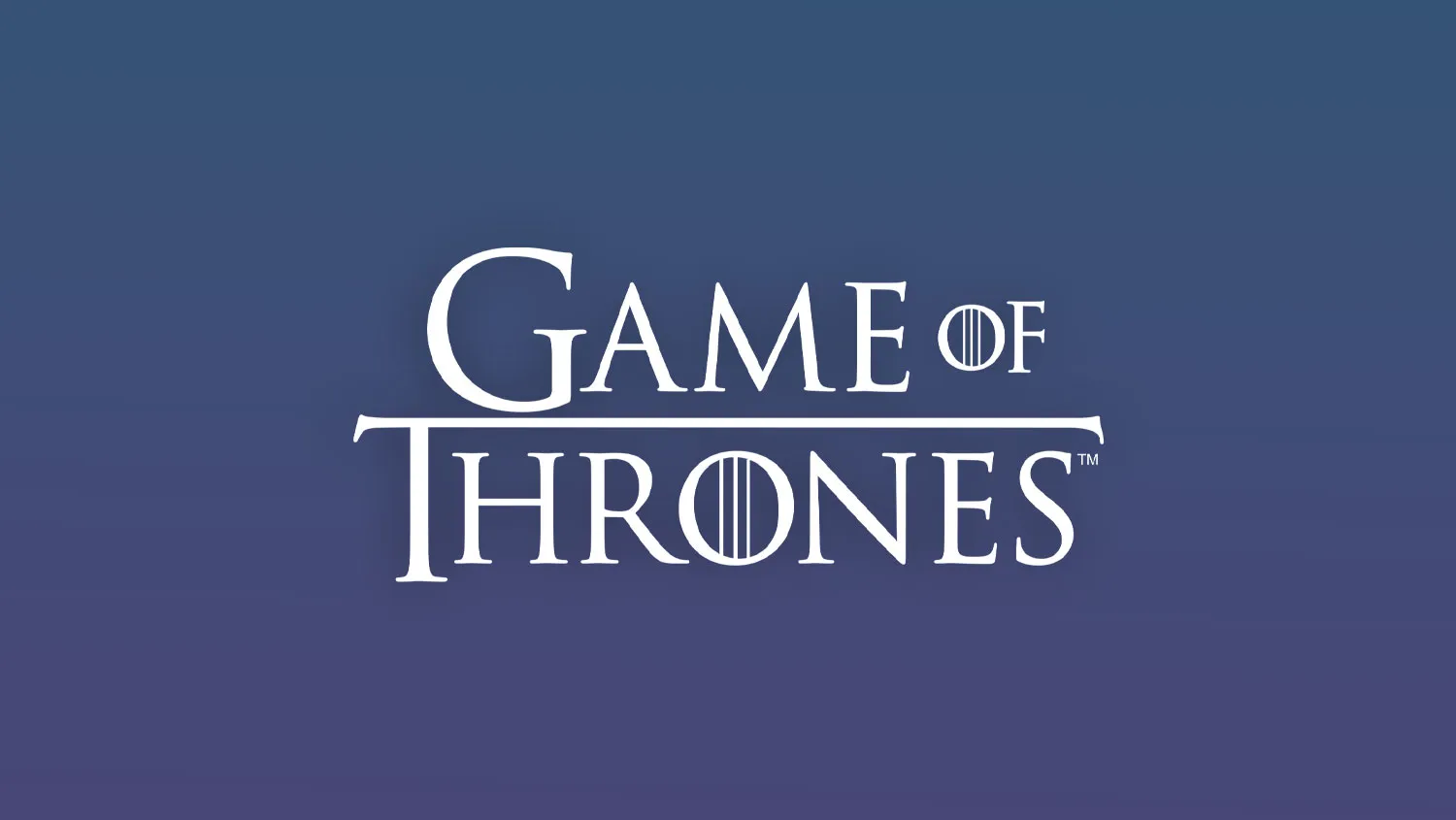
I font delle serie tv più famose
Vediamo insieme cosa si nasconde dietro i font di alcune delle serie tv più famose. Font e logotipi che hanno contribuito in qualche modo a rendere queste serie iconiche, da Stranger Things a Game of Thrones, da Dottor House a Breaking Bad. Scopriamoli insieme.
Stranger Things
Stranger Things è un capolavoro in tutto e per tutto, anche dal punto di vista tipografico. L’idea era quella di ricordare i mitici anni ’80, tanto nelle sceneggiature, nei costumi e nelle musiche, quanto nelle scritte.
Stranger Things
La sigla, comprensiva di titolo e nomi degli attori, è stata realizzata dall’agenzia di design Imaginary Forces. Il loro compito era ben preciso: ricreare un’atmosfera di fantascienza anni ’80, traendo ispirazione da una quindicina di copertine di libri, prime fra tutte quelle di Stephen King.
Il titolo e famosissimo logo della serie tv è stato scritto con un font realizzato da Ed Benguiat, l’ITC Benguiat, mentre per i nomi degli attori è stato utilizzato il font ITC Avant Garde.
Font delle serie tv: Game of Thrones
Non riusciamo a immaginare niente di più iconico del titolo di testa di una delle serie tv più amate e seguite di sempre: Game of Thrones. La serie tv si è anche aggiudicato l’Emmy Awards per il miglior design dei titoli di testa, nel 2011, l’anno di uscita della prima stagione.
Game of Thrones
Eppure è incredibile pensare che quel font, che è riuscito a conquistare tutto il pubblico e che ha portato la serie alla vincita di un Emmy, altro non è che una versione modificata di uno dei font più utilizzati al mondo: il Trajan.
L’attuale versione di questo font è quella del designer di font Carol Twombly, risalente al 1989. Tuttavia, essa trae ispirazione alle incisioni rinvenute alla base dalla colonna traiana innalzata a Roma nel secondo secolo dopo Cristo.
Lo stesso font è stato successivamente utilizzato nella campagna elettorale di Donald Trump, ma la HBO non ha gradito tale “furto”.
Breaking Bad
La sigla di Breaking Bad è probabilmente la sigla che ha vinto più titoli in assoluto, con un totale di 94 premi vinti nel suo settore e 240 nomination.
Breaking Bad
La sigla utilizza due diversi tipi di font: l’Arial MT Bold e il Bundy. L’Arial è uno dei font più distribuiti, utilizzati e diffusi al mondo.
Nella sigla è stato utilizzato per descrivere i due elementi della tavola periodica che compongono le prime sillabe delle due parole del titolo: Breaking Bad. I due elementi sono rispettivamente il Bromio e il Bario.
Il resto della scritta utilizza, invece, il font Bundy.
Font delle serie tv: Twin Peaks
Torniamo indietro negli anni, fino al 1990, quando negli Stati Uniti va in onda la prima stagione di Twin Peaks.
Twin Peaks
La sigla parte con la scritta del titolo della serie tv accompagnata dalla colonna sonora di Angelo Badalamenti. Il font utilizzato è l’ITC Avant Garde Gothic di un colore verde acido.
I due elementi, il font e il colore, collidono, creando un’atmosfera da una parte tranquilla e dall’altra straniante.
Dottor House
Ma fa un certo effetto anche il titolo della serie, scritto utilizzando il font Futura, creato da Paul Renner e considerato il pioniere dei font sans serif geometrici.
Font delle serie tv: The Mentalist
Infine, concludiamo con la serie tv The Mentalist.
The Mentalist
Per la sigla è stato utilizzato, anche in questo caso, uno dei font più famosi e diffusi: l’Helvetica, classico, elegante, essenziale ed estremamente leggibile. Il tutto accompagnato dalla colonna sonora di Blake Neely.